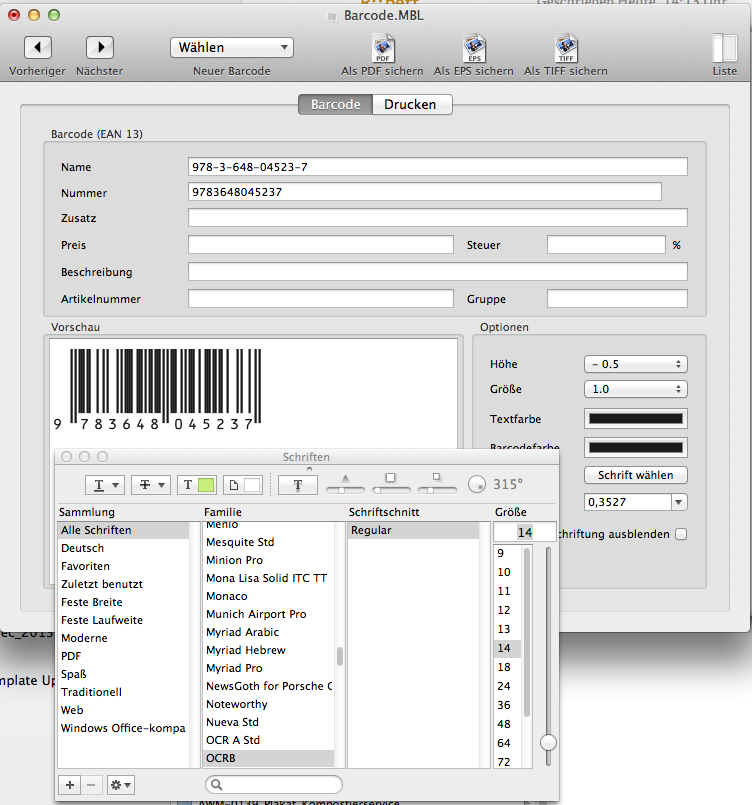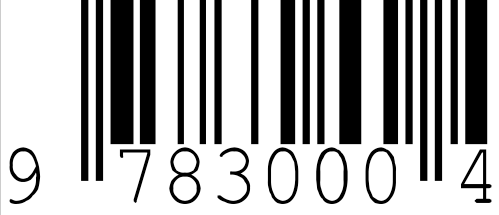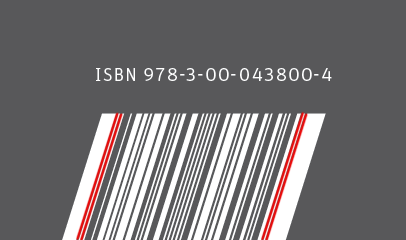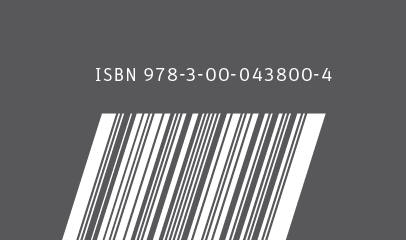
Schrift des ISBN-Strichcode ändern?
habe soeben den ISBN-Strichcode für ein Buch bekommen. Die Schrift ist furchtbar. Kann man diese in so einem Fall (wenigstens in eine OCR) ändern, oder wie würdet Ihr in so einem Fall verfahren?
Natürlich. Der Text ist ja die menschenlesbare Variante, die in der Regel nicht von Maschinen gelesen werden muss.  :huhu:
"Gute" Barcodeprogramme bieten dir beim Erstellen eine Schriftwahl an, beispielsweise:
und wenn du ganz kreativ sein willst, kannst du noch die kanten des barcodes nachträglich trimmen oder sonstwie erweitern, wenn’s denn zum thema des buches passt. ein paar beispiele hier.
Der eigentliche Barcode (also die Striche) ist maschinenlesbar und lebt allein von der Breite der kontrastierenden Striche. Die Höhe ist völlig egal, daher können die Codes auch so ungewöhnliche Formen wie von Calito gepostet bekommen.
Die Zahlen dienen allein der Möglichkeit, den Artikel von Hand ins Kassen-, Lager oder sonstige System zu bringen, wenn kein Barcodescanner vorhanden, das Label verknittert oder sonstwie unlesbar geworden ist. Dann kommt der Mensch ins Spiel und muss die Zahlen der Reihe nach eintippen, wobei die letzte Zahl eine errechnete Prüfziffer ist und nicht frei vergeben werden kann. Der eigentliche Code ist also streng genommen eine Ziffer kürzer.
Alles soweit klar. Mich beschlichen lediglich Zweifel, da ja (sicher nicht umsonst) unter zahlreichen Strichcodes häufig die »maschinenlesbaren« OCR-Schriften zu Einsatz kamen/kommen (und die Schrift von meinem Beispiel evtl. einem ähnlichen Standard entspringt). Aber möglicherweise ist das inzwischen nicht mehr nötig.
Könnte mir vielleicht noch jemand sagen, ob folgende Lösung funktioniert?:
Ich habe etwas Bauchschmerzen, weil die Striche invers dargestellt sind.  :-? Gestalterisch wäre das aber eleganter.
Das wird nicht zuverlässig funktionieren, weil nicht jede Scannersoftware invertieren kann. Sobald ein EAN-Code außerhalb eures Systems gelesen werden muss (egal ob Aldi oder Buchhandlung oder ARAL …) werden nicht-invertierte vorausgesetzt.
Bei QR-Codes können das manche QR-Reader mittlerweile (da ist’s auch egal, wenn sie nicht funktonieren), EAN-Codes müssen aber zuverlässig sein.
Braucht’s nicht. Die Scannersoftware richtet sich immer nach der ersten und letzten schmalen Doppellinie, rot markiert. Sobald die erkannt werden, wird der Code erkannt.
Braucht’s doch!
Bei einem EAN13-Code (der ja auch für die ISBN verwendet wird), muss vor dem Linken Randzeichen ein Freiraum von der 11 fachen Breite der schmalsten Linie (X-Modul genannt) und nach dem Randzeichen ein Freiraum von der 7 fachen Breite weiß (bzw. für rotes Licht hell - also auch rot) bleiben. Ist der ganze Code also 31,35mm breit (X-Modul 0,33) muss der linke Freiraum mindestens 3,63, der rechte 2,31 mm breit sein.
Inverse Darstellung ist nicht erlaubt, wohl aber Farben, die bei rotem Licht für die Linien dunkel sind, also schwarz, blau, grün oder dunkles braun, für die Freiräume dann hell (helle Linien) dann rot, orange, gelb oder weiß.
Für Ladenkassen und Freihandscanner sollten die dünnsten Linien 0,264 mm sein, was zu einer Breite des EAN-Codes incl der Hellzonen 29,83mm beträgt
Braucht’s doch!
Warum jetzt das? Sein EAN-Code funktioniert doch einwandfrei und der Freiraum vor dem linken Randzeichen ist doch groß genug?
Weil das eben so in den Design-Richtlinien für EAN-Codes so drin steht. Möglicherweise funktionieren viele Scanner auch mit abweichenden Werten, aber garantiert ist das dann eben nicht.
Aber bei den letzten Beispielen kommt es ja, außer das hier wohl die rechte Seite den breiteren Freiraum hat, wohl in etwa mit den Normwerten hin.
Weil das eben so in den Design-Richtlinien für EAN-Codes so drin steht. …
Ich kapier es nicht … sein EAN-Code entspricht den Richtlinien, ist lesbar und trotzdem muss er den linken Weißrand vergrößern?
In deinem Beitrag #18 klang es, als wäre überhaupt kein Rand nötig. Das ist in dieser Absolutheit sicher falsch – ohne Rand keine Linien.
Catfonts hat nur nachgereicht, dass es zum Rand konkrete Empfehlungen gibt. Das ist doch hilfreich.
Zudem habe ich ja auch nicht behauptet, das dieser garantiert nicht funktioniert. Je moderner die Scanner sind, um so eher kommen sie mit nicht ganz Standardgerechten Barcodes zurecht.
Allerdings habe ich auch schon mit transparenter roter Farbe auf Silber gedruckten Barcode gesehen (, der dann natürlich an der Kasse für eine längere Schlange sorgte, da zudem auch noch der Klartext fehlte. Was der Gestalter dieser Verpackung sich dabei gedacht hat, ist mir gänzlich unklar.